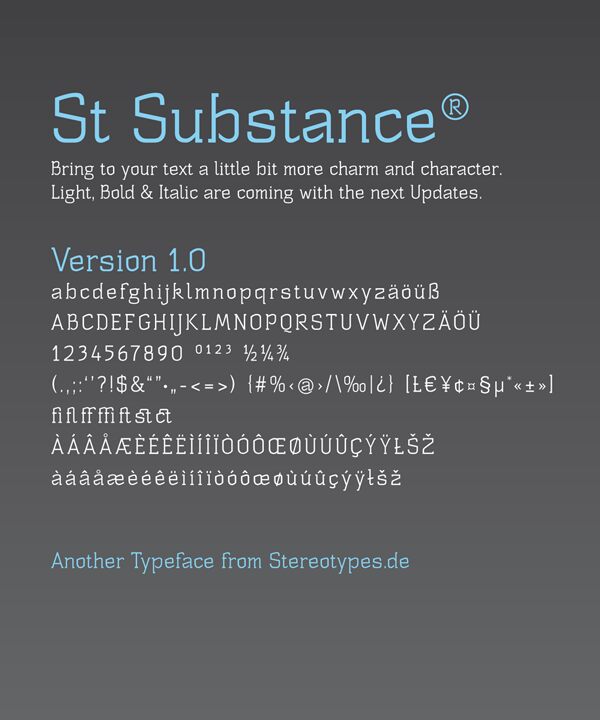
ST Substance autorstwa Saschy Timplana to bezpłatny, nowoczesny krój szeryfowy typu display o niezwykle smukłej, architektonicznej budowie. Wysokie litery, ostre narożniki i nagłe zmiany grubości linii nadają projektowi surowy, redakcyjny charakter. Formy są oszczędne, ale nie delikatne.